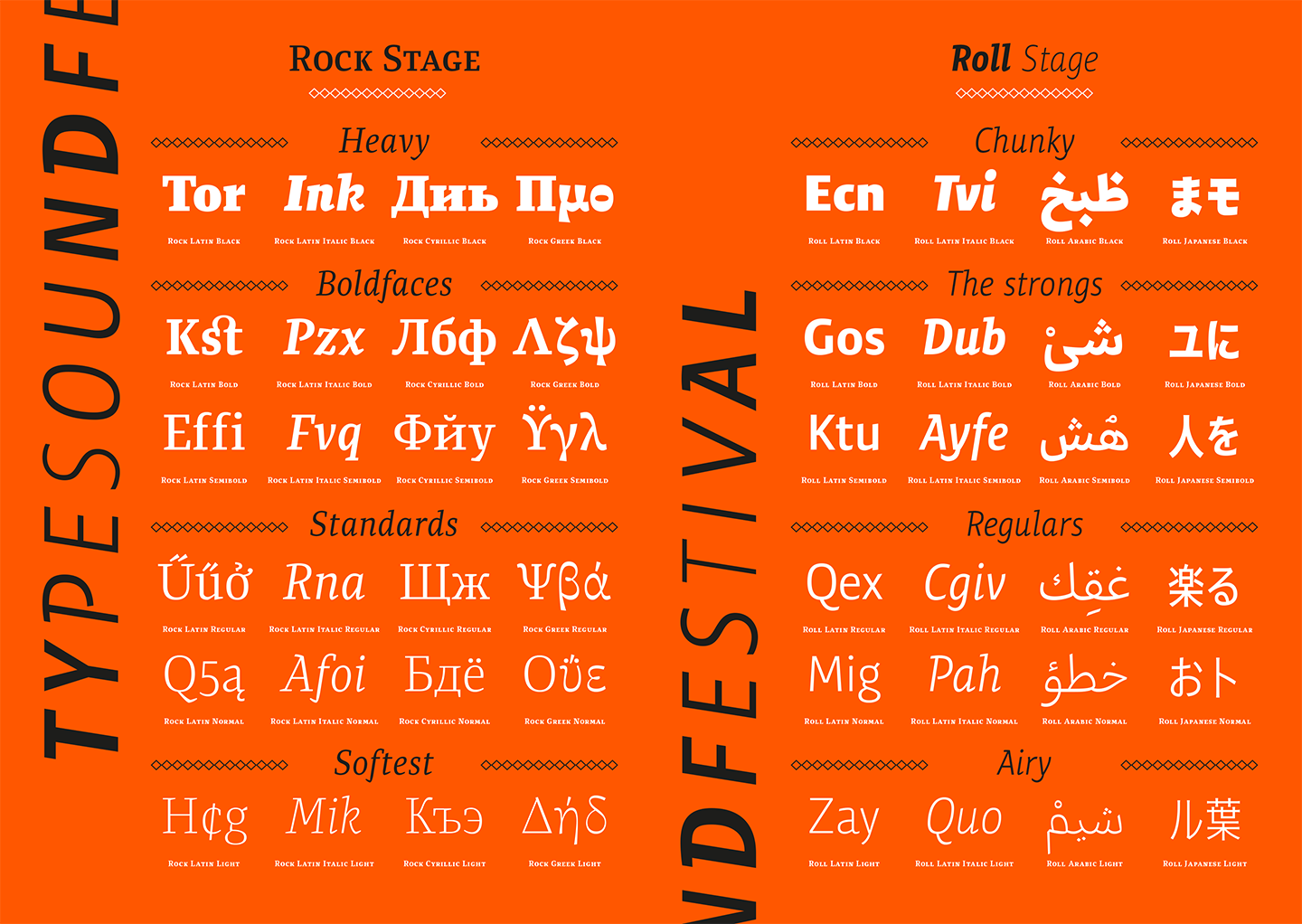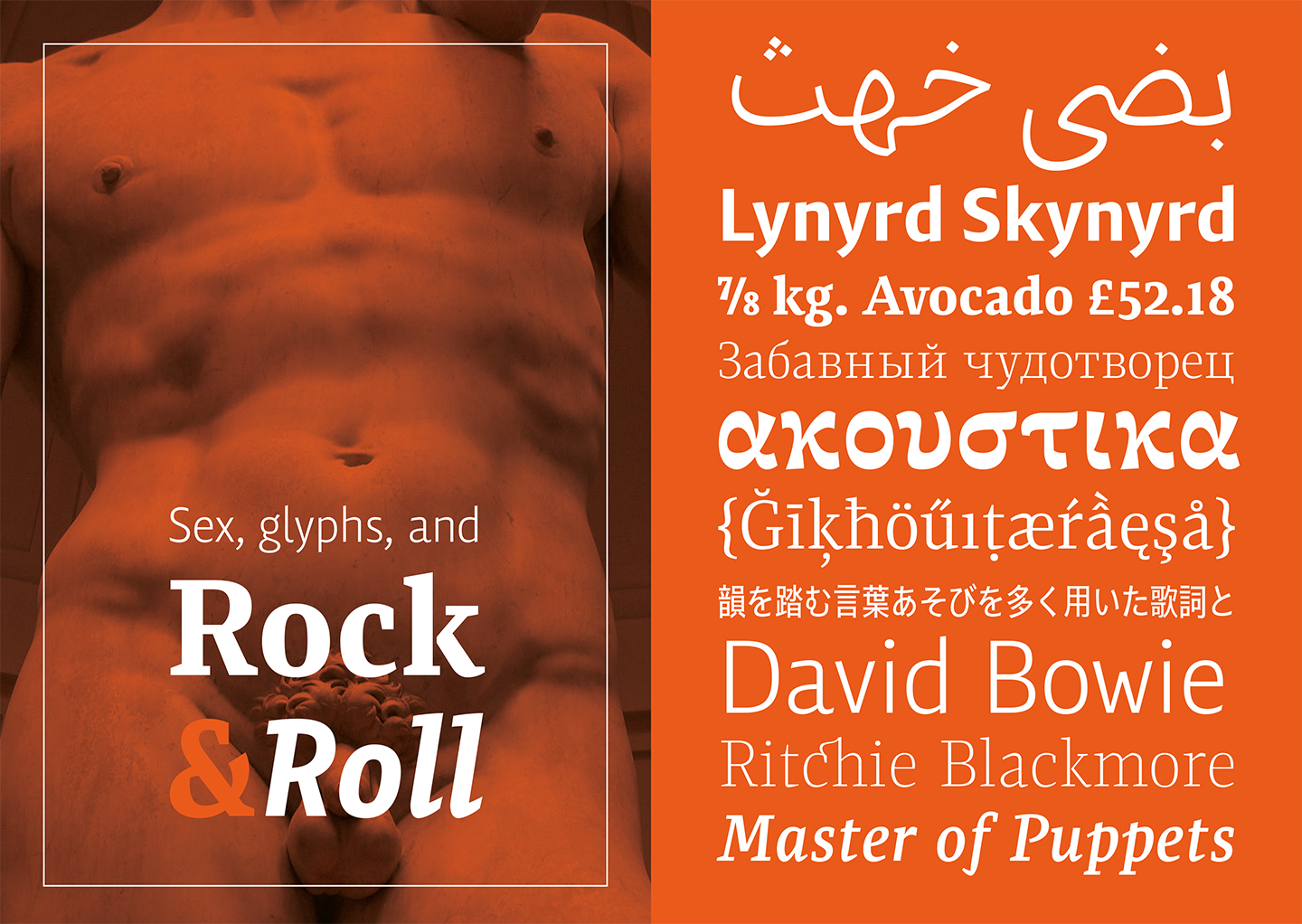
Pedro Arilla, a pesar de su juventud, es ya un referente indiscutible en el panorama tipográfico español por su incansable actividad desde hace años. Divulgador a través de su propio blog, Don Serifa, artífice junto a Damiá Rotger del intensivo y pasional curso de tipografía Glíglifo y, por supuesto, diseñador de tipos. Sin embargo, Arilla quería seguir avanzando, profundizando, quizá convencido de que la tipografía es una disciplina en la que nunca se deja de aprender. Por eso, un buen día hizo las maletas y se encaminó a tierras inglesas para cursar el MA Typeface Design en la facultad de Typography & Graphic Communication de la Universidad de Reading, quizá una de las dos o tres titulaciones más prestigiosas —y exigentes— del mundo a nivel tipográfico, lo que le ha brindado la oportunidad, una vez completado el máster, de trabajar nada menos que en Fontsmith.
Sobre todo ello, y un poco más, hemos charlado con este joven aunque más que sobradamente preparado diseñador tipográfico. La idea consiste en acercarnos, a través de la experiencia directa de algunos diseñadores españoles, a los más sólidos y prestigiosos cursos internacionales de tipografía, de modo que podamos descubrir que, en realidad, Europa, tipográficamente hablando, no está tan lejos.
Rayitas Azules: Hace unos años, concretamente en 2012, escribías en un tu blog, Don Serifa, un artículo sobre estudiar tipografía en Europa y hablabas del máster de Reading diciendo que «es un curso que incluye un elemento práctico importante para dotar al alumno con los conocimientos necesarios para diseñar y producir sus propios tipos de letra a través de una sólida base histórica y teórica. Uno de los puntos más interesantes es que se hace especial hincapié en los tipos de letra no latinos, caso del árabe, el hebreo o el cirílico». ¿Seguirías destacando estas cualidades del máster o, ahora que los conoces desde dentro, añadirías alguna más a la hora de explicar en qué consiste el curso?
Pedro Arilla: ¿En 2012 decía eso? Sí, podría ser; pero ahora que he estado dentro, la percepción que tengo de master es más compleja y colorida. Es cierto que se da mucha importancia a los tipos multi-escritura —y, de hecho, es obligatorio diseñar al menos un sistema que no sea el tuyo nativo— y que algunos de los mayores expertos del mundo, como Fiona Ross, están ahí. Pero el espectro de materias que cubre es muy amplio: tallado en piedra, caligrafía, historia, impresión tipográfica, programación, tipografía (no diseño de tipos) y hasta pinceladas de arquitectura y movimientos sociales. La tipografía y la escritura son ámbitos tan estrechamente relacionados con la evolución del ser humano, que sería un error ceñirse al mero diseño de caracteres. Pero lo que hace realmente especial a este máster —y a otra casi media docena que hay repartidos por el mundo, me atrevería a decir— es que respiras tipografía 24 horas al día y aprendes de y con alumnos y profesores de distintas edades, procedencias y trayectorias.
RA: ¿Cómo es ahora Pedro Arilla después de Reading?
PA: En lo personal: todavía más consciente de que el mundo es enorme. En lo tipográfico: con una visión más amplia y global. Ambos conceptos, como ves, van unidos de la mano. Pero, en general, con la confirmación bajo el brazo de que el enfoque adecuado es nunca olvidar que todos somos estudiantes, nunca maestros.
RA: Se dice, se comenta, que es imprescindible un buen nivel de inglés para cursar el máster. ¿Ha sido difícil para ti manejarte en inglés con los conceptos puramente técnicos?
PA: Cierto es que, aunque vayas con un nivel de inglés medianamente decente, no siempre te puedes expresar como quisieras y eso es dolorosamente frustrante. Así que recomiendo encarecidamente darle durísimo al inglés ante de ir. Y, centrándonos en lo tipográfico, es verdad que, a veces, te encuentras con que no sabes decir, por ejemplo, «cartela» pero, al fin y al cabo, no es tan complicado porque no son tantísimos términos. Si te soy sincero, creo que lo más difícil eran los nombres de diseñadores. Por ejemplo, me costó unos veinte minutos entender que Michael Twyman estaba hablando de Jan Tschichold.
RA: ¿Qué destacarías del máster que más te haya llamado la atención?
PA: Lo que más me ha explotado la cabeza ha sido la manera de aproximarse al diseño de tipos como disciplina y como industria. Hay muchas maneras de atacar un problema; o un prisma se puede observar desde diferentes de perspectivas. Aquí se cubren todas ellas desde la observación, reflexión y exploración. Diseñar tipos y producir fuentes se puede aprender de una manera más o menos sencilla; en cambio, aprender a pensar es más complejo. No es casual que de Reading hayan salido en las últimas décadas algunas de las figuras tipográficas que más se han cuestionado nuestro oficio y, por tanto, ayudado a que evolucione.
RA: ¿Qué consejos le darías a una persona que estuviera interesada en estudiar en Reading? ¿Qué se necesita, además de muchas ganas (dinero, organización, tiempo…)?
PA: En cuanto al consejo: aprender mucho antes de ir. Yo, por ejemplo, me estuve preparando durante seis años para ir a Reading. Sin descanso. Mi objetivo era vencer mis ganas por ir cuanto antes y ser paciente para, una vez ahí, dedicarme a escalar un peldaño más y aprender de una manera mucho más profunda. Es una profesión extensa y compleja (como todas) por lo que yo decidí ir con la base bien aprendida y superada. Allí quería que me exprimieran. Creo que fue una decisión acertada.
En cuanto al resto de cosas que mencionas, de dinero estaríamos hablando de 7.000 libras por el máster, más lo que cuesta vivir allí. De tiempo: un año completo (de septiembre a septiembre). Organización: toda la que puedas. Ya que vas a dedicar un año de tu vida a hacer algo, hazlo bien. Hay gente que no lleva muy bien el volumen de trabajo y el nivel de exigencia de un máster de estas características, porque además de todas las asignaturas y tareas concernientes al diseño de tipografía, hay que hacer un segundo trabajo final de máster, en este caso de investigación. En realidad es un máster que debería durar más de un año (y así fue pensado) pero que dura lo que dura, así que mejor saber organizarse, disfrutar del viaje y picar piedra día tras día sabiendo que eres un afortunado por estar ahí.
RA: Háblanos un poco e Rock & Roll, tu última tipo, como proyecto final de máster.
PA: Cada vez leemos más y más en dispositivos móviles con estructuras tipográficas complejas y en pantallas de una resolución cada vez mayor. Con Rock & Roll exploré las posibilidades que eso ofrecía en términos de expresividad y legibilidad. Quería tallar formas con luz y hacerlo de forma que la familia tipográfica resultante fuese lo suficientemente interesante. Así pues, Rock es una tipo con contraste que cubre los sistemas de escritura latino (el que utilizamos en español), cirílico y griego; Roll es una tipo sin contraste que soporta latino, árabe y japonés. Son estos dos últimos sistemas de escritura con los que más me divertí. Estoy muy interesado en temas como legibilidad y comportamientos visuales y, honestamente, creo que el mayor logro que el diseño de tipos ha alcanzado en los últimos cinco siglos es hacer creer al cerebro que sus ojos nunca le van a engañar. Explorar esa máxima en un proyecto que responde a tus propias reglas y bajo sistemas de escritura que no son los tuyos nativos, es un lujo que merece la pena vivir.
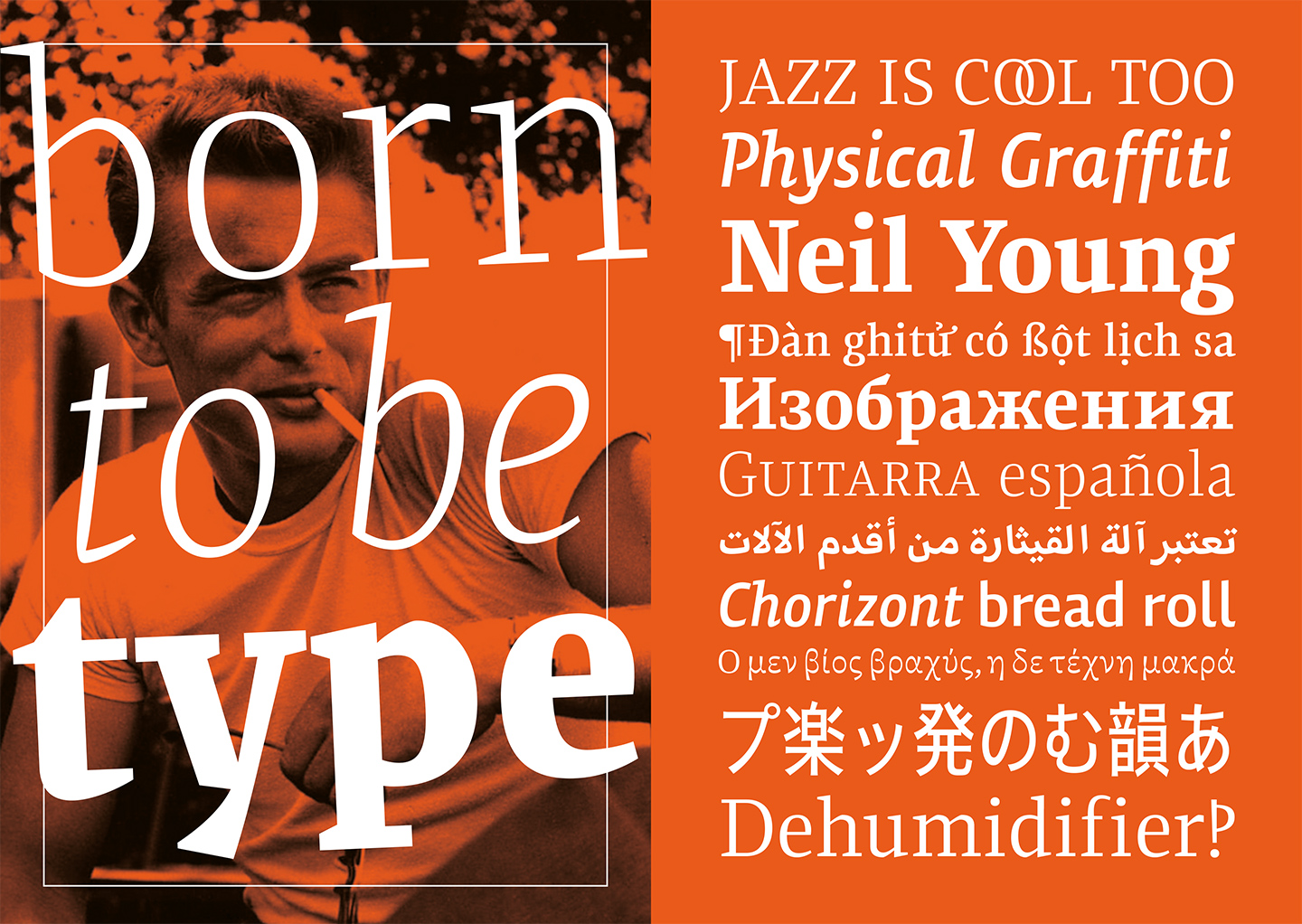
PA: La tipografía siempre forma parte de las decisiones que tomo pero esta en concreto va más allá. He vivido 32 años en España, he tenido trabajos maravillosos y tengo amigos a los que quiero y que me quieren. Pero esa es una vida que ya he vivido. Como no creo en la reencarnación, mudarme —mudarnos, más bien— a Londres y empezar de cero es la única manera de vivir una segunda vida. La muerte es lo único que tenemos asegurado, así que pienso vivir todas las vidas que pueda antes de que ese día llegue. ¿Por qué conformarse con la que nos arrastra al aquí y ahora?